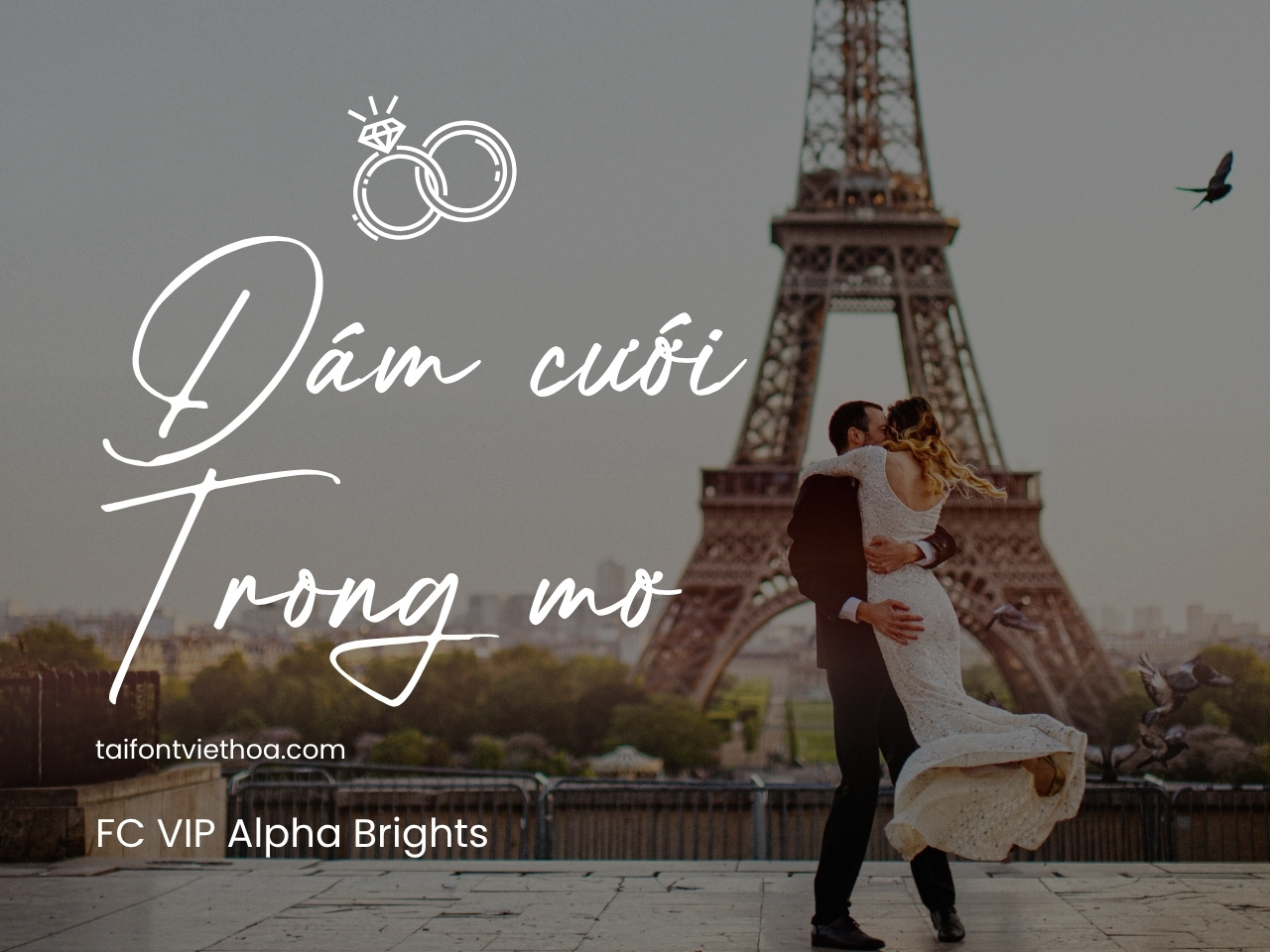
Giới thiệu về font Alpha Brights và bản Việt hóa
Alpha Brights là một font chữ viết tay cao cấp được phát triển bởi Typeline Studio – một nhà thiết kế nổi tiếng chuyên về các kiểu chữ thư pháp hiện đại. Với sự kết hợp giữa phong cách hand-lettering nghệ thuật và cấu trúc mảnh mai, mềm mại, Alpha Brights thể hiện cảm xúc mạnh mẽ qua từng đường nét uyển chuyển. Font ban đầu được phát hành trên các nền tảng như Creative Market và đã hỗ trợ hơn 60 ngôn ngữ trong hệ Latin mở rộng.
Phiên bản FC VIP Alpha Brights đã được cộng đồng Font Chuẩn Việt hóa hoàn chỉnh, tích hợp đầy đủ bảng chữ cái tiếng Việt với các dấu thanh chuẩn xác, giữ nguyên tinh thần mềm mại và linh hoạt vốn có. Bản Việt hóa đã được taifontviethoa.com tuyển chọn và cập nhật nhằm đáp ứng nhu cầu ngày càng cao của nhà thiết kế trong việc tìm kiếm font chữ vừa cảm xúc vừa phù hợp cho các dự án sáng tạo mang bản sắc Việt.
Phong cách thiết kế ấn tượng và các lĩnh vực ứng dụng của Alpha Brights
Alpha Brights thuộc nhóm font viết tay (handwritten), được thể hiện bằng các đường nét cong tinh tế, tự nhiên như bút lông hoặc viết tay thủ công. Từng ký tự mang đến cảm giác như được viết bằng tay thật sự, với độ nghiêng nhẹ và đường dẫn chuyển mượt mà. Chính đặc điểm này khiến font dễ dàng hòa hợp với các thiết kế thiên về cảm xúc như thiệp mời, chữ ký số, ảnh cưới hoặc lời chúc lễ hội.
Font này đặc biệt phù hợp cho các ngành nghề như tổ chức sự kiện, truyền thông thương hiệu, ảnh cưới, thiệp cưới, làm đẹp, thiết kế thiệp chúc mừng và sản phẩm sáng tạo cá nhân. Ngoài ra, Alpha Brights cũng là lựa chọn lý tưởng trong các thiết kế quảng cáo dịp Tết, Valentine, Sinh nhật hoặc thương hiệu cần nhấn mạnh cảm xúc thân mật và cá tính riêng biệt.